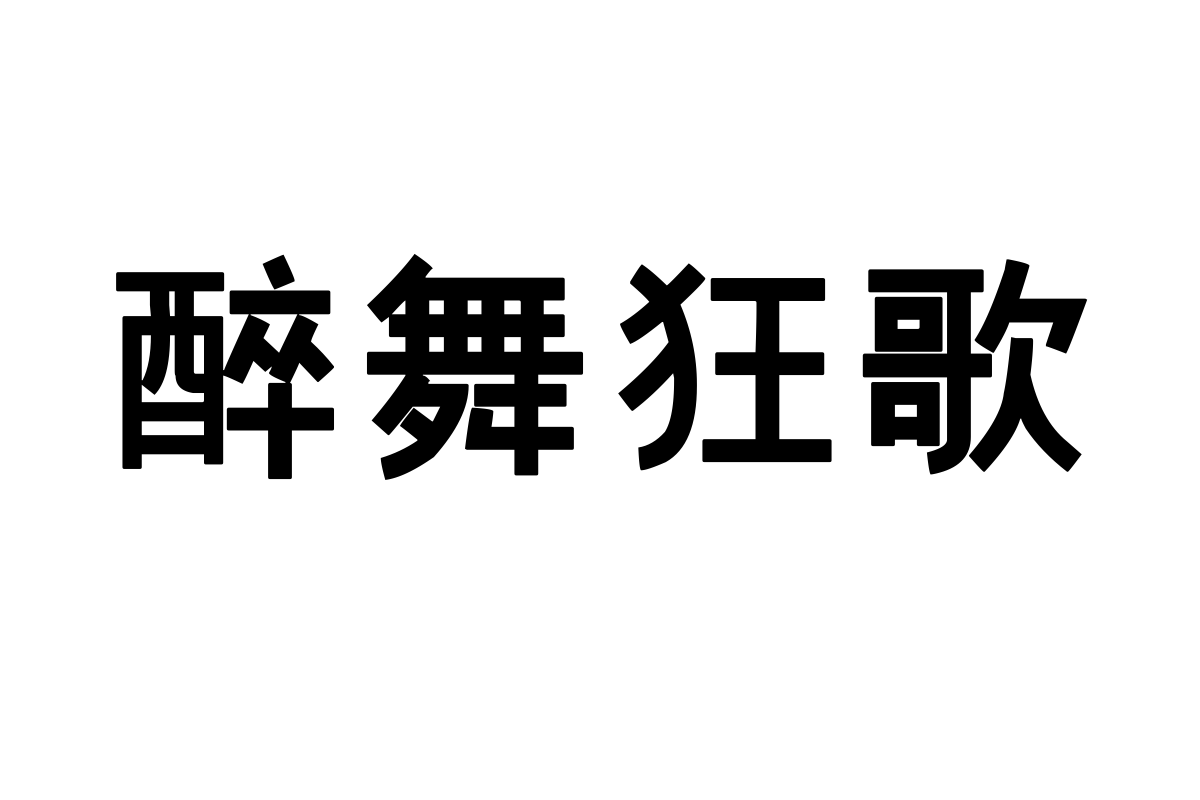
汉标粗黑体是一种常见的中文字体,由汉标字体公司设计。这种字体的特点是字形粗壮、笔画粗细均匀,给人一种强烈的视觉冲击感。它广泛应用于各种印刷品和电子屏幕上的文本显示,如报纸、杂志、广告、网站等。
汉标粗黑体的笔画粗细适中,既有力度又不失柔和,适合用于需要强调的文字表达。同时,它的字形结构紧凑,线条流畅,易于阅读和识别,是制作标题、正文等文字内容的理想选择。
总的来说,汉标粗黑体是一种实用且具有强烈视觉冲击力的字体,适用于多种场合的文字设计需求。